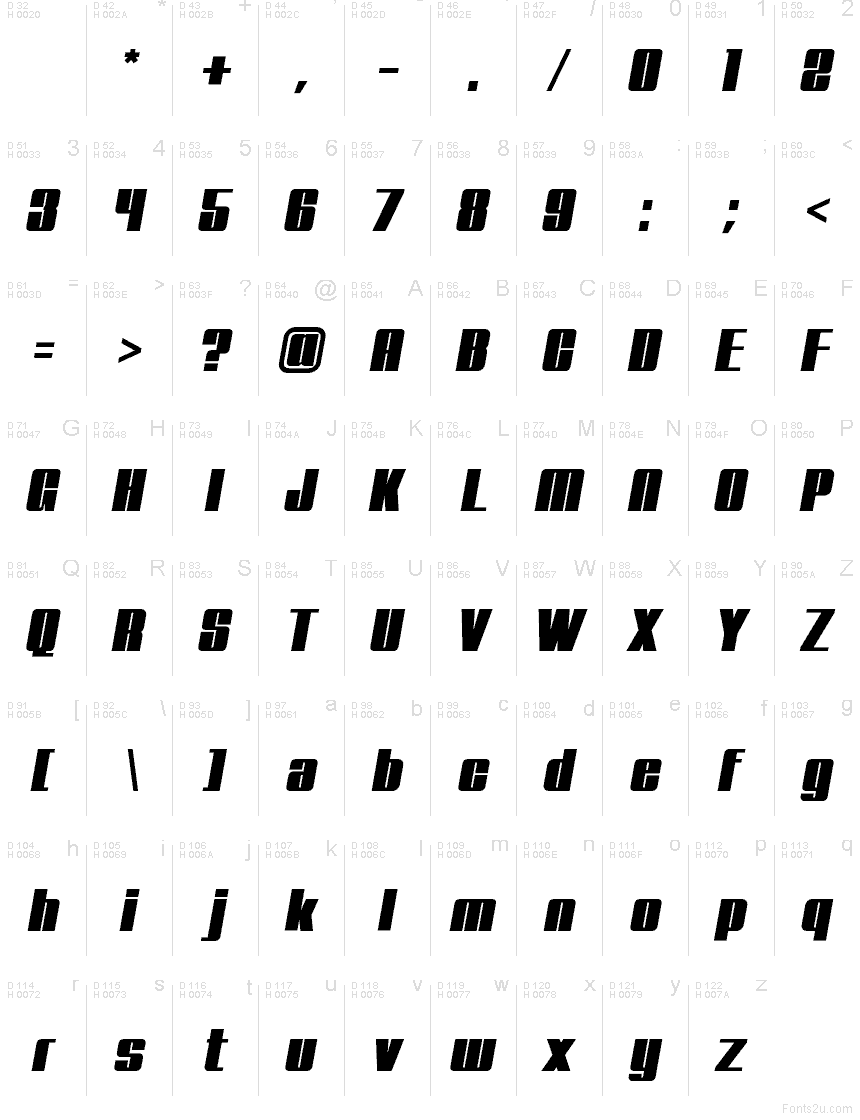
Gordi Oblique von Afkari Studio ist eine kostenlose Retro-Display-Schrift mit einer rasanten, geneigten Silhouette und dem unverwechselbaren Flair der späten 70er Jahre. Die Buchstaben wirken wuchtig und kompakt, doch die feinen vertikalen Aussparungen verleihen der Schrift eine gestreifte, dynamische Struktur, die an klassische Beschilderungen und filmische Titelsequenzen erinnert.
Sie ist ideal für Poster-Überschriften, Plattencover, Verpackungen, Logokonzepte und Magazin-Titel, bei denen dieser nostalgische Schwung voll zur Geltung kommt. Als kostenlose Schrift eignet sie sich zudem hervorragend für Titelkarten und kurze Branding-Elemente, da der geneigte Stand und die in den Lettern verlaufenden Linien selbst kurzen Worten einen authentischen Zeitgeist verleihen.